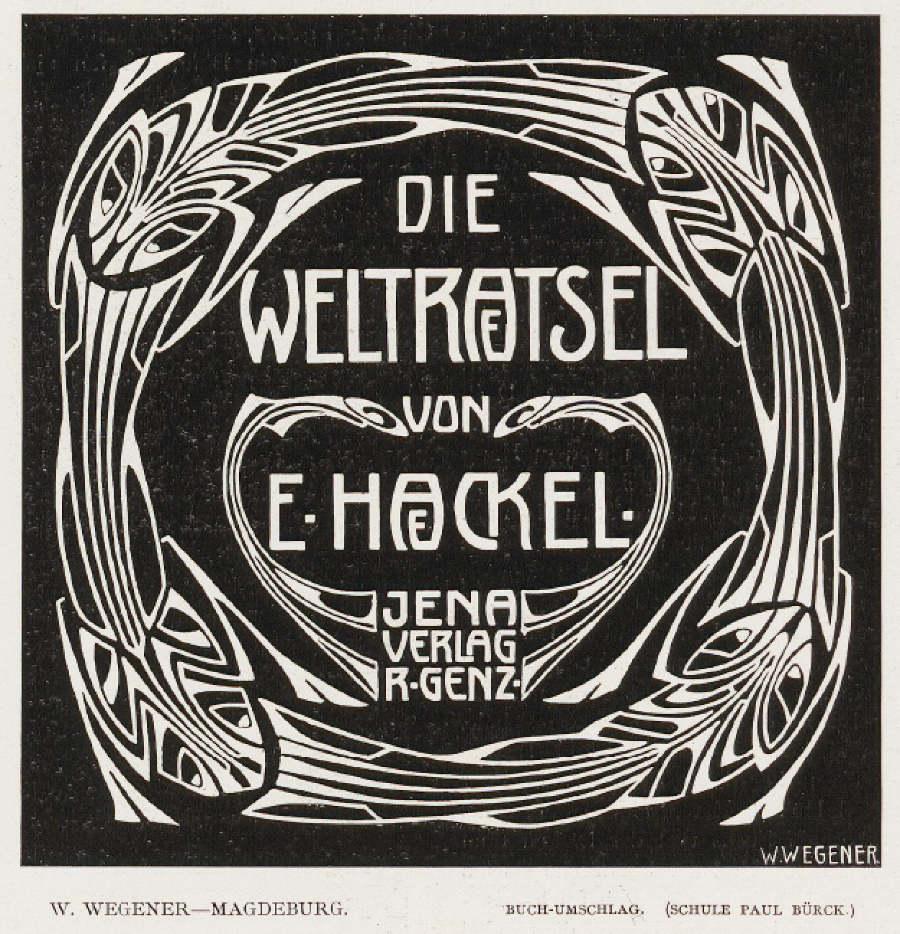
Im konkreten Beispiel ist die Ligatur schon etwas irritierend eingesetzt. Bei »Welträtsel« wird das »ä« und bei »E. Haeckel« das »ae« durch die Ligatur »ae« ersetzt.
Thema  Ä / AE.
Erinnere mich dunkel, bei meiner Ausbildung zum Fernschreiber beim BGS ( in den 60ern
des vorigen Jahrhunderts)  gelernt zu haben: bei Eigennamen ist der Umlaut zu vermeiden.
Es sei denn das ist durch die amtliche Schreibweise  vorgegeben.  Ansonsten ist der  Umlaut
durch  E- Anhang zu bilden. Auf dem Siemens T68  - - mobiler Streifen- Springschreiber - -
war das  ohnehin nicht anders machbar; der hatte nur Kleinbuchstaben und Zahlen.  Beim  T 100
- -  stationärer Blattschreiber - -  war das natürlich  auch nicht anders, wegen der  Signalkompa-
tibilität.  Und meine, das sollte auch bei Beurkundungen so  gehalten werden.
Die Bedienung eines Fernschreibers hat aber nur bedingt etwas mit Typografie zu tun, die Regeln sind doch komplett andere.
Bezog mich auch nur auf die  unterschiedliche Anwendung
bei Haekel  und Rätsel.  Wg " Eigennamen".
Daß Typografie als Kunstform nicht  behörd-
lichen  Regelungen folgen muß, ist mir auch klar.
Thema  Ä / AE. …
Schick! Wo hast Du das gute Stück denn aufgegabelt?  Und paß auf, daß Dir die zwei Anwälte nicht wegen diesem Bild an den Karren fahren :lol:
Klassisch im Antiquariat ... online. :-)
Da sind Musterwörter die mir liegen ... die links noch mehr als die rechts. 🥃
(Die Schriftmuster stammen übrigens aus einer Email von Commercial Type.)